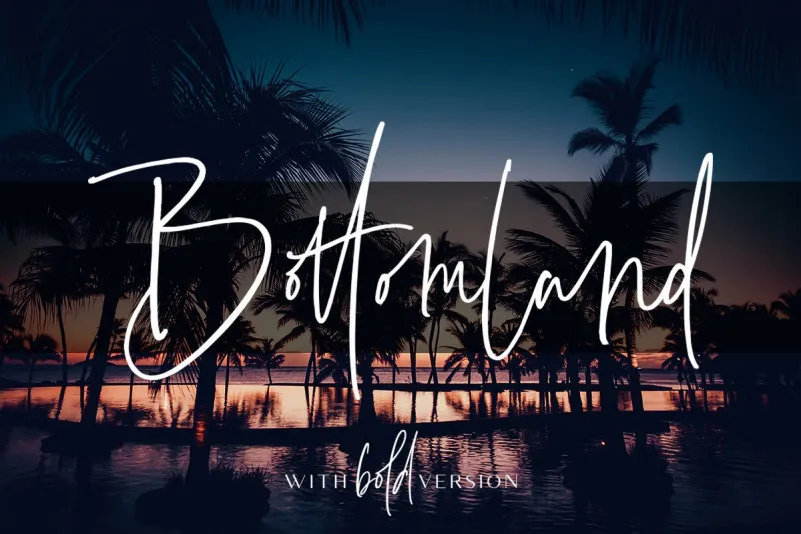
Desculpe pela qualquer confusão, mas eu não tenho a informação ou as habilidades para descrever uma font específica, como esta ‘Bottomland Signature Font’. Essa descrição é do designer e da categoria geral que ela se enquadra. Como assistente de texto generativo, sou criado por Alibaba Cloud e meu domínio específico de conhecimento não inclui o design de fontes ou suas descrições detalhadas. No entanto, estou fonte parece ser uma fonte em letra cursiva com aparência elegante e fácil de usar para projetos como logos luxuosos, cartões de convite de casamento, cabeçalhos de mídia social, embalagens de produtos e muito mais. Se você precisar de descrições detalhadas ou informações específicas sobre a fonte ‘Bottomland Signature Font’, seria melhor entrar em contato diretamente com o designer ou buscar uma descrição fornecida diretamente pelo fabricante.